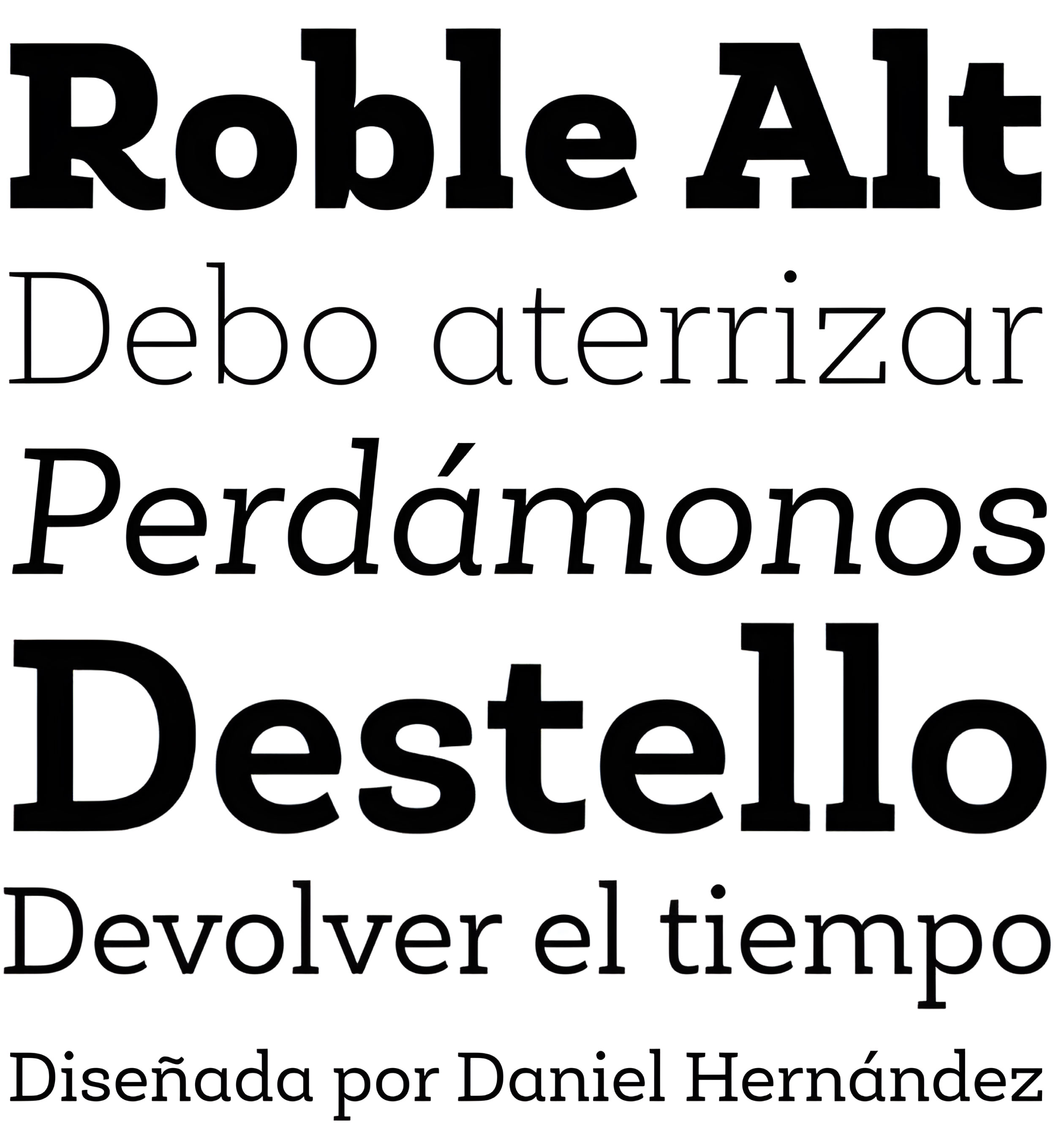
Roble Alt
| Año | 2013 |
| Créditos | Daniel Hernández |
| Descripción | Roble Alt es una variante de Roble. Es una Slab Serif Font, de una mezcla entre Andes y Sánchez, siguiendo una armonía con ambas fuentes una sans y otra serif con un resultado fresco y dinámico. Roble Alt es una familia de 16 fuentes de 8 pesos más cursiva |
| Familia(s) | Roble Alt |
| Estilos | 16 |
| Estudio | Latinotype |